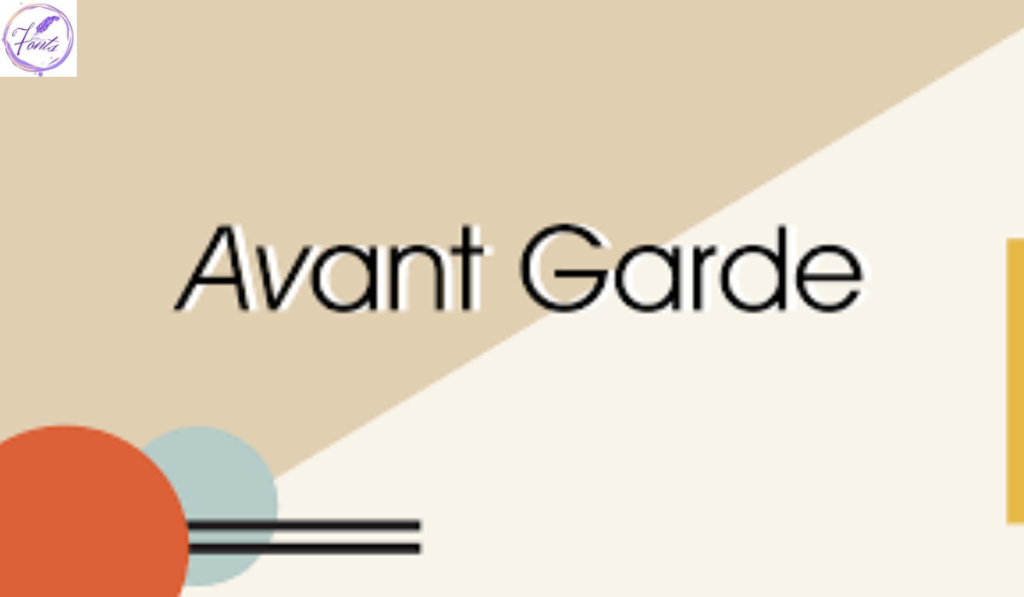
Font Avant Garde việt hóa
Tác giả: Herb Lubalin, Tom Carnase
Ngày phát hành: 1970
Bộ Font: Avant Garde
Phân loại: Cá tính, Độc đáo, Hiện đại
Kiểu chữ: sans-serif
Độ dày: Book, Demi, Demi Oblique, Book Oblique
Font Avant Garde Việt hóa là sự mở rộng từ phông chữ Avant Garde nổi tiếng, được thiết kế với mục đích mang đến sự tinh tế và hiện đại cho mọi thiết kế. Với bản việt hóa, font này bao gồm đầy đủ các ký tự tiếng Việt, giúp các nhà thiết kế tại Việt Nam dễ dàng áp dụng trong các dự án từ in ấn đến kỹ thuật số. Phông chữ này được ưa chuộng trong việc tạo các tiêu đề, logo và các ứng dụng thiết kế đòi hỏi sự sang trọng và nổi bật.